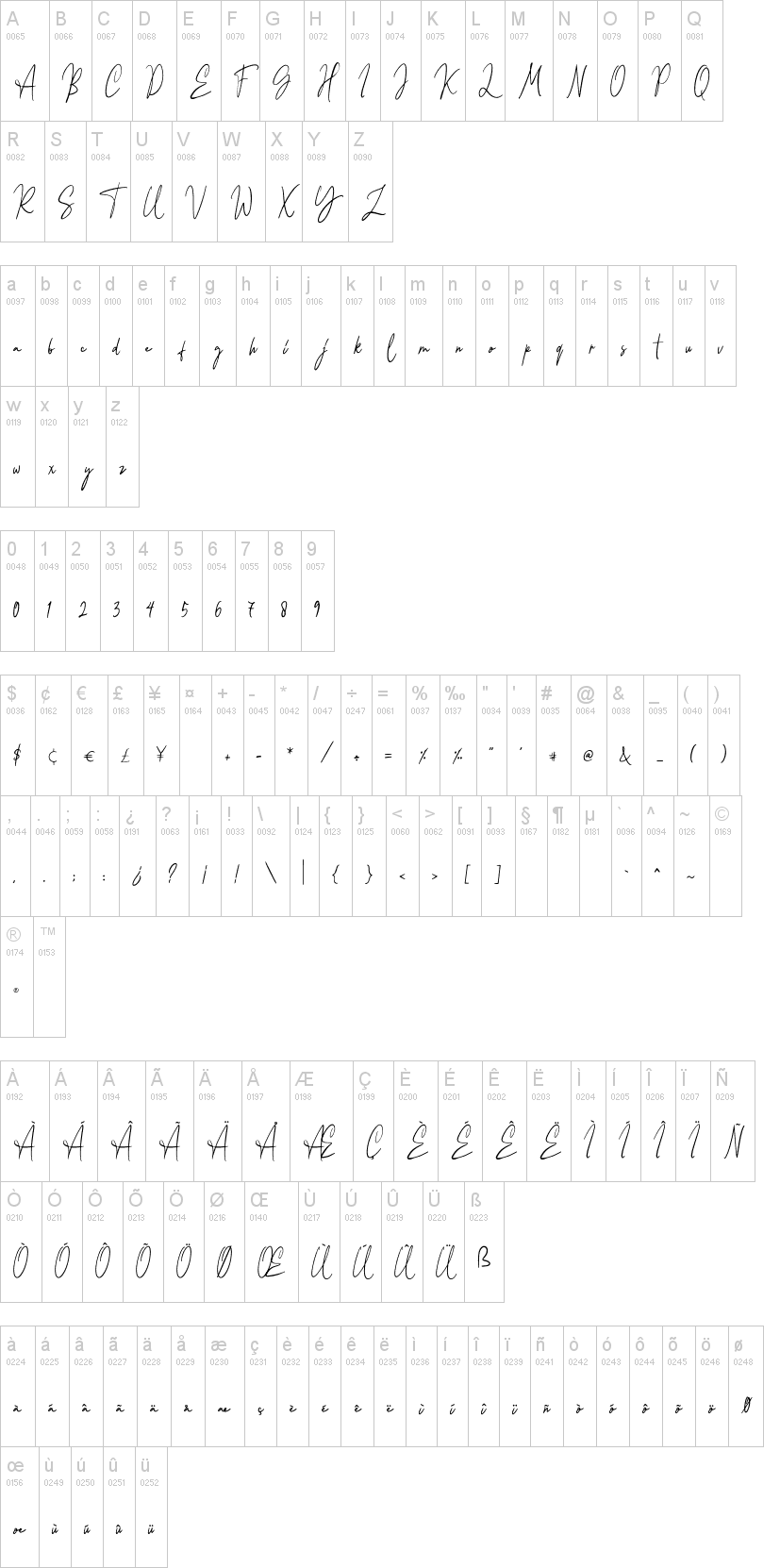
Baliestan 是一种非常漂亮和流畅的字体,由 Saffatin co. 设计制作。该字体旨在为电影标题、标志、海报、书籍封面等设计项目提供视觉吸引力。 Balietan 字体具有非常明显的斜体和粗体版本,非常适合用于强调和突出重点。此外,它还包含了许多特殊字符和符号,使其非常适合用于多种语言和文化。该字体可用于个人和商业项目,也可以在许可证下使用。总之,Balietan 是一种非常优秀的字体,可为您的设计项目增添独特的风格和美感。内容介绍
Balietan是一款非常不错的手写艺术字体,具有很好的视觉感,适合于文化类的宣传设计、商业类品牌的广告和产品包装设计以及个性化文字排版等较多场景。